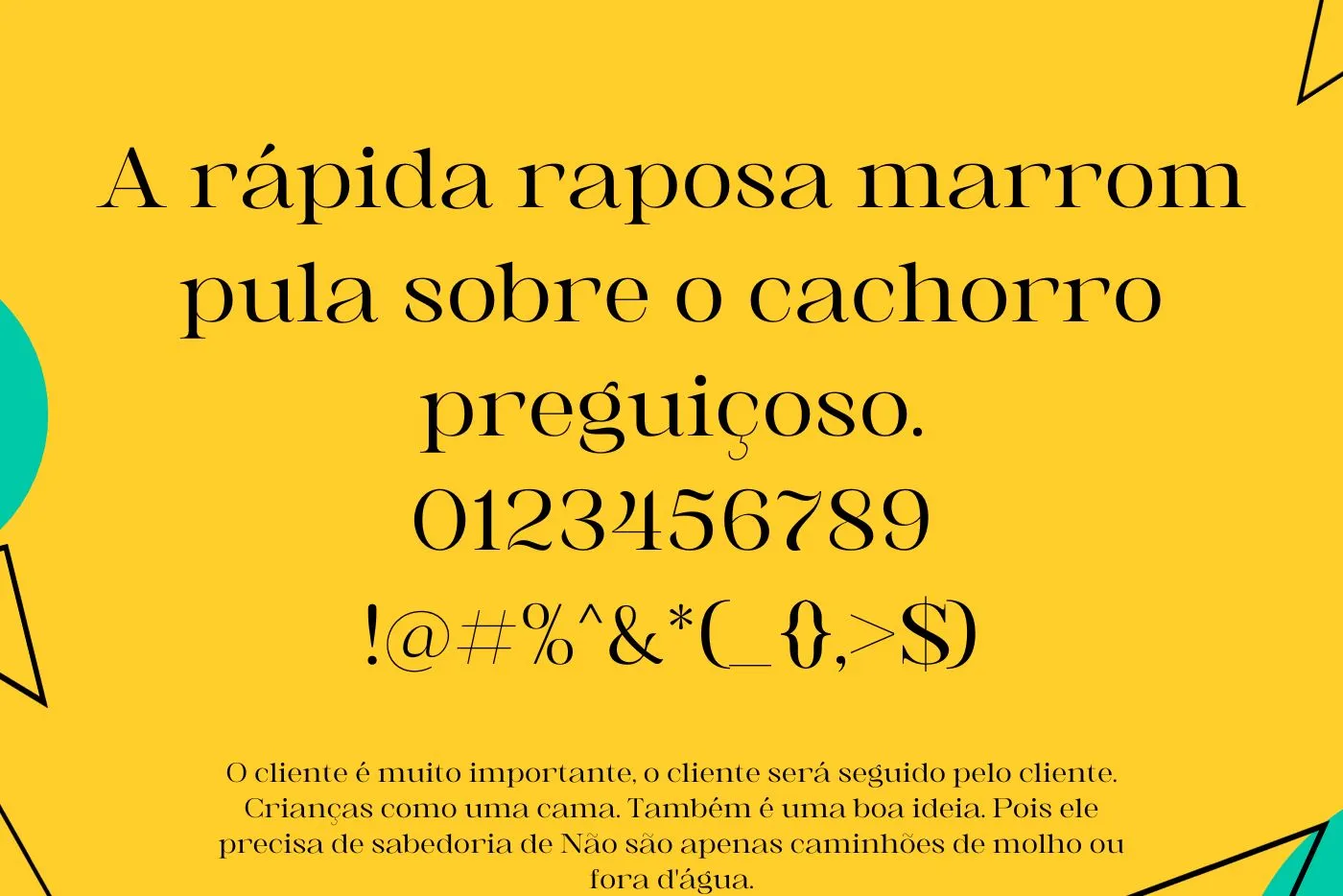
A fonte Awaken é uma fonte serifada elegante. É projetado pelo StringLabs Creative Studio e traz sofisticação e um toque clássico. Com suas características distintivas, destaca-se em diversas aplicações gráficas. Esta fonte combina elementos de tipografia clássica com um toque contemporâneo, tornando-a adequada para uma variedade de contextos criativos.
Uma das principais características é sua seriedade e legibilidade. Os caracteres são desenhados com traços sólidos e bem definidos, sendo uma excelente opção para títulos, cabeçalhos e corpo de texto em materiais impressos e digitais. Esta família de fontes é melhor para usar com o emparelhamento de uma fonte semelhante, como a fonte Matane, que está disponível gratuitamente aqui. Seus detalhes cuidadosamente elaborados, como as elegantes terminações da haste e as serifas sutis, conferem um ar de requinte ao design.
O seu estilo intemporal faz com que se destaque em projetos que primam por uma estética clássica, enquanto a sua legibilidade o torna uma escolha prática para comunicações claras e eficazes. Com ele você tem a combinação perfeita de elegância e funcionalidade ao seu alcance.
Recurso Principal da Fonte Awaken
A principal característica é a capacidade de transmitir uma sensação de elegância e sofisticação em qualquer projeto de design. Com suas linhas bem definidas e detalhes cuidadosamente elaborados, esta fonte é especialmente indicada para criar um ambiente clássico e refinado. É bom para uso em fins de design mais atraentes, combinando com a fonte Valorant, que é uma fonte gótica.
É versátil, funcionando bem em uma variedade de contextos criativos. A sua excepcional legibilidade também é destaque, garantindo que a mensagem seja comunicada de forma clara e eficaz. No geral, sua principal característica é a capacidade de adicionar um toque de sofisticação e estilo atemporal a qualquer projeto de design.
Família de Fontes Awaken
- Awaken Regular
Aplicações da Fonte Awaken
- Cabeçalhos de sites e blogs com um toque moderno e elegante.
- Materiais promocionais, como cartazes e banners, para chamar a atenção.
- Convites de eventos, dando um ar sofisticado aos detalhes.
- Logotipos e marcas, transmitindo uma sensação de contemporaneidade.
- Materiais impressos, como cartões de visita e folhetos, para destacar informações.
- Design de embalagens, proporcionando uma estética diferenciada.
- Redes sociais, criando posts visualmente atraentes.
- Projetos de design de interiores e decoração, para personalizar elementos.
- Em combinação com a fonte Barlow, você pode criar apresentações, transmitindo uma imagem moderna.
- Publicações digitais e impressas, mantendo uma estética consistente.
Qual é a fonte da fonte Awaken?
É uma fonte serifada elegante. É projetado pelo StringLabs Creative Studio e traz sofisticação e um toque clássico.
Qual é o melhor uso da fonte Awaken?
Seu melhor uso é para projetos que buscam transmitir elegância e sofisticação, como títulos, textos de display, convites de casamento, materiais luxuosos e peças de design clássico.